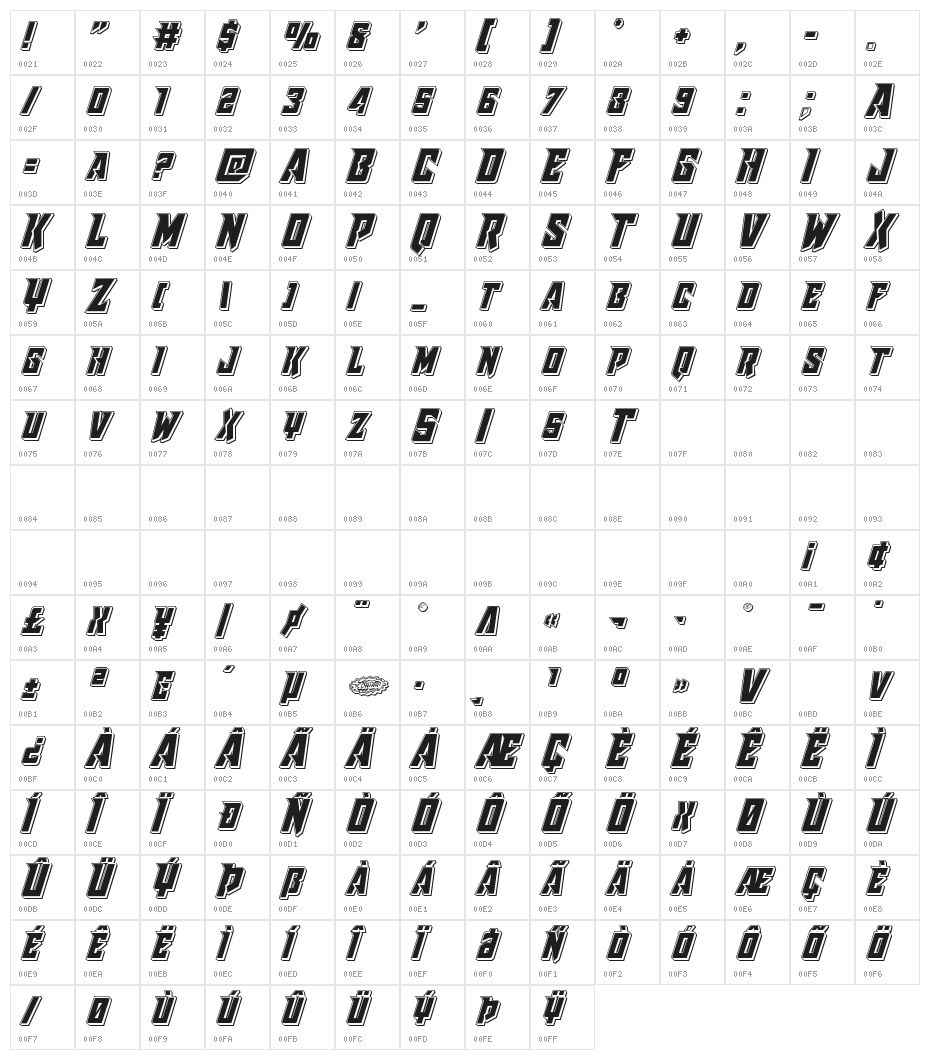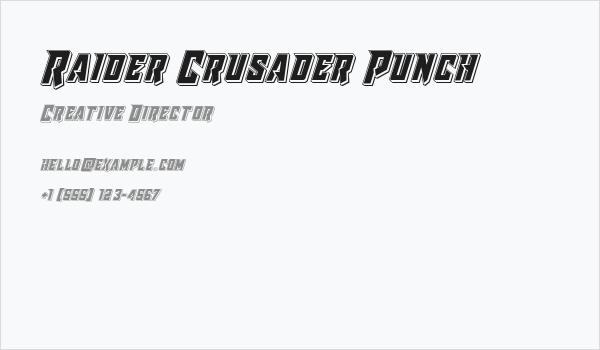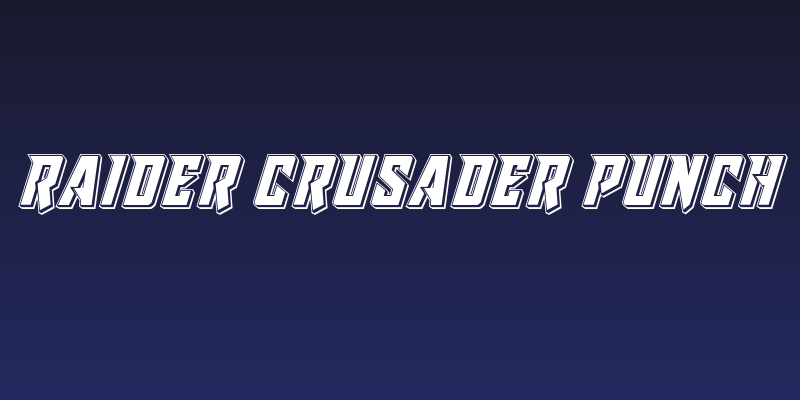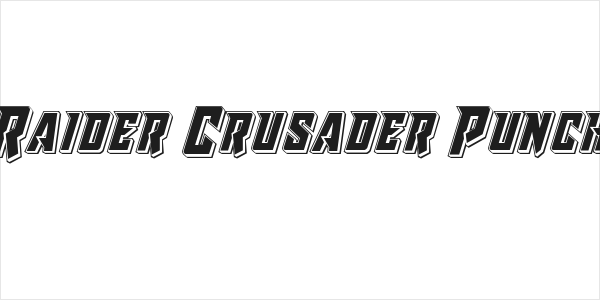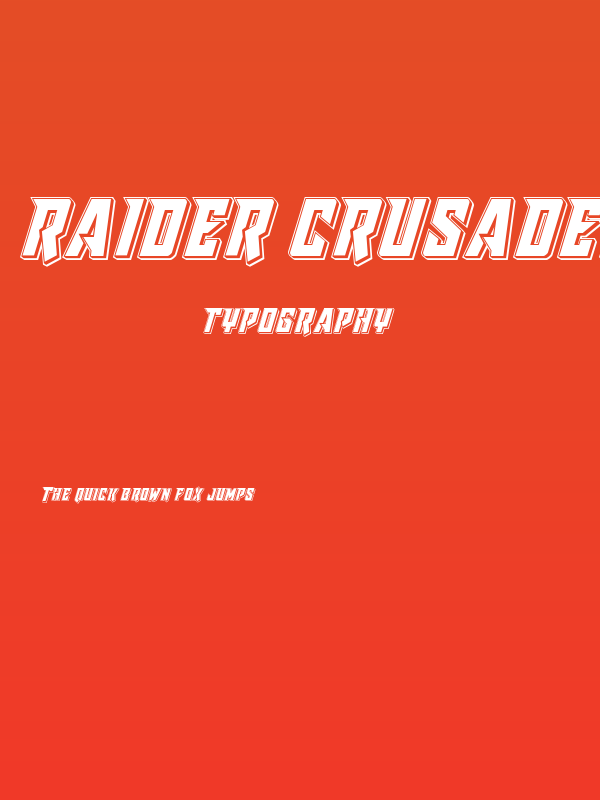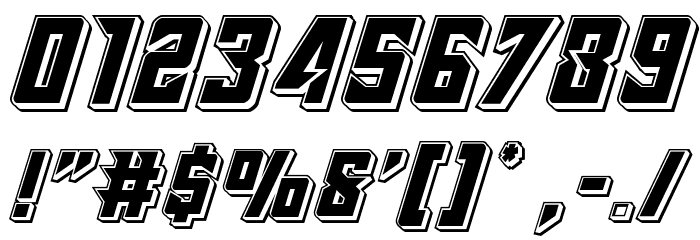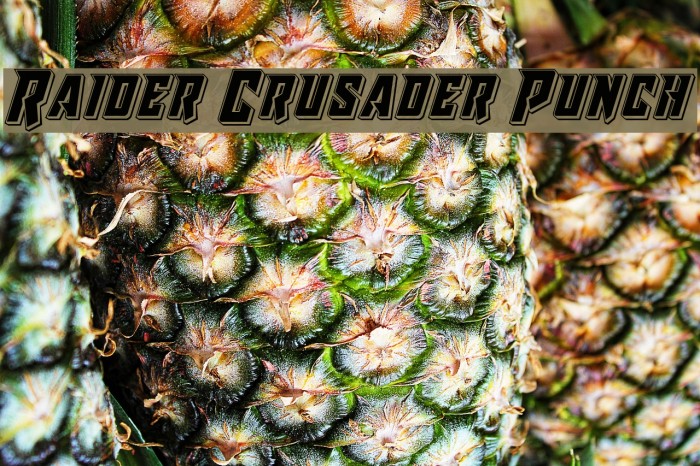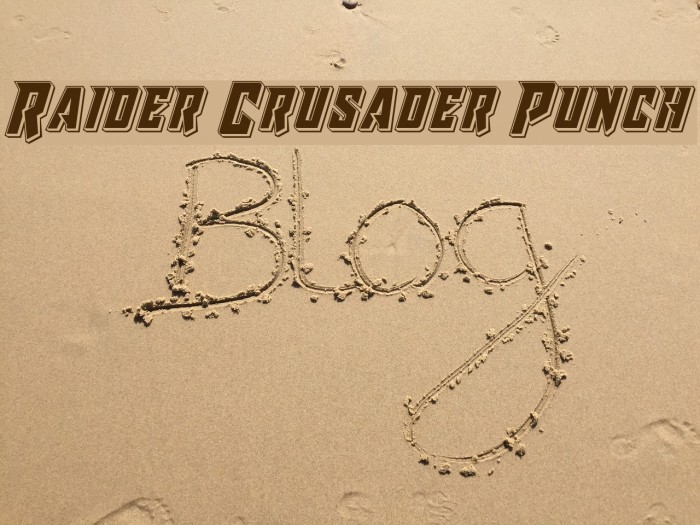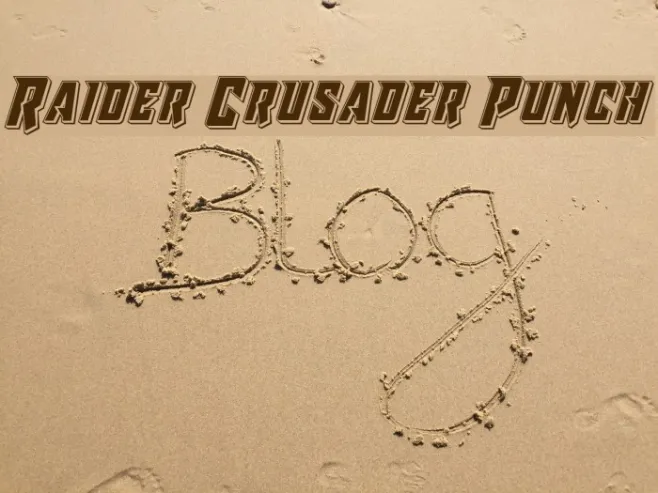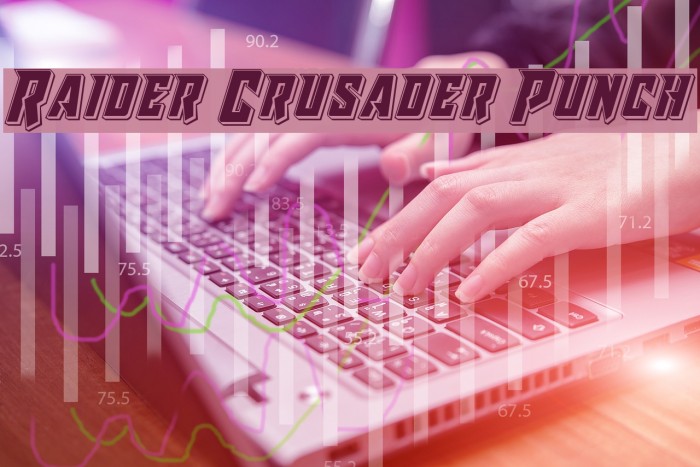
Raider Crusader Punch Font
| Nom | Raider Crusader Punch |
| Catégories | 3D |
| Style général | Modern, Dynamic |
| Projets proposés | Ideal for sports team logos, event posters, video game titles, and any project needing a bold, impactful typeface. |
| Auteur | Fonts by Casady & Greene |